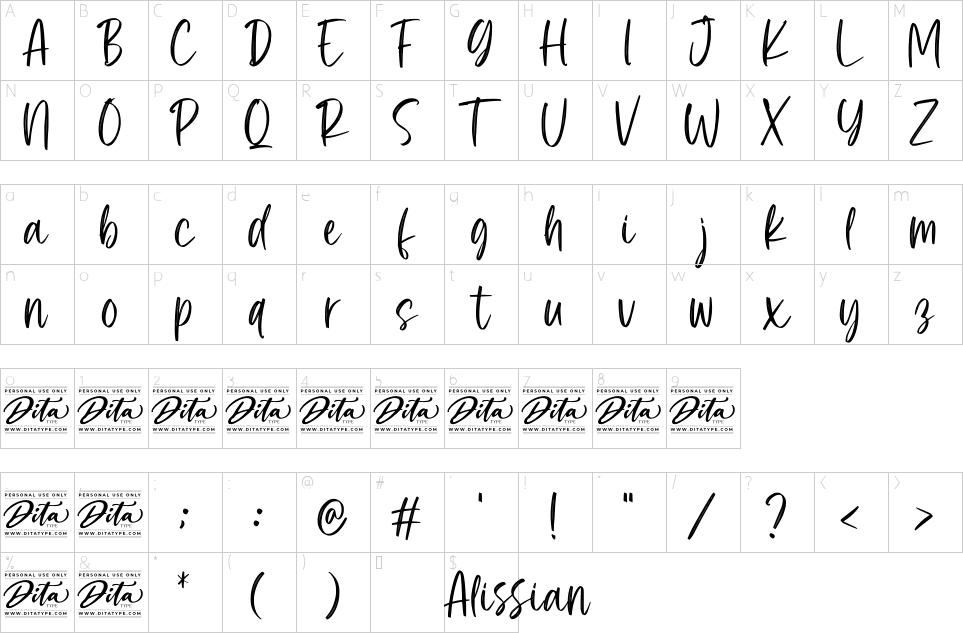
Alissian Font – Fonte Grátis
Alissian Font
Descubra a Alissian, uma elegante e moderna fonte que traz um toque de sofisticação ao seu design. Esta fonte foi criada pelo designer Dita Type e é uma escolha ideal para quem procura uma fonte fresca e versátil para projetos digitais e impressos. Alissian foi projetada para oferecer um equilíbrio perfeito entre legibilidade e beleza visual, sendo especialmente apropriada para aplicativos de escrita, sites, materiais gráficos e identidades visuais. Desde seu lançamento, a fonte Alissian já foi descarregada por 2.624 usuários, demonstrando seu valor e popularidade entre criadores de materiais digitais. Se você está procurando por uma fonte gráfica de alta qualidade que seja tanto uma versão elegante quanto prática, a Alissian pode ser a escolha perfeita para seus projetos.